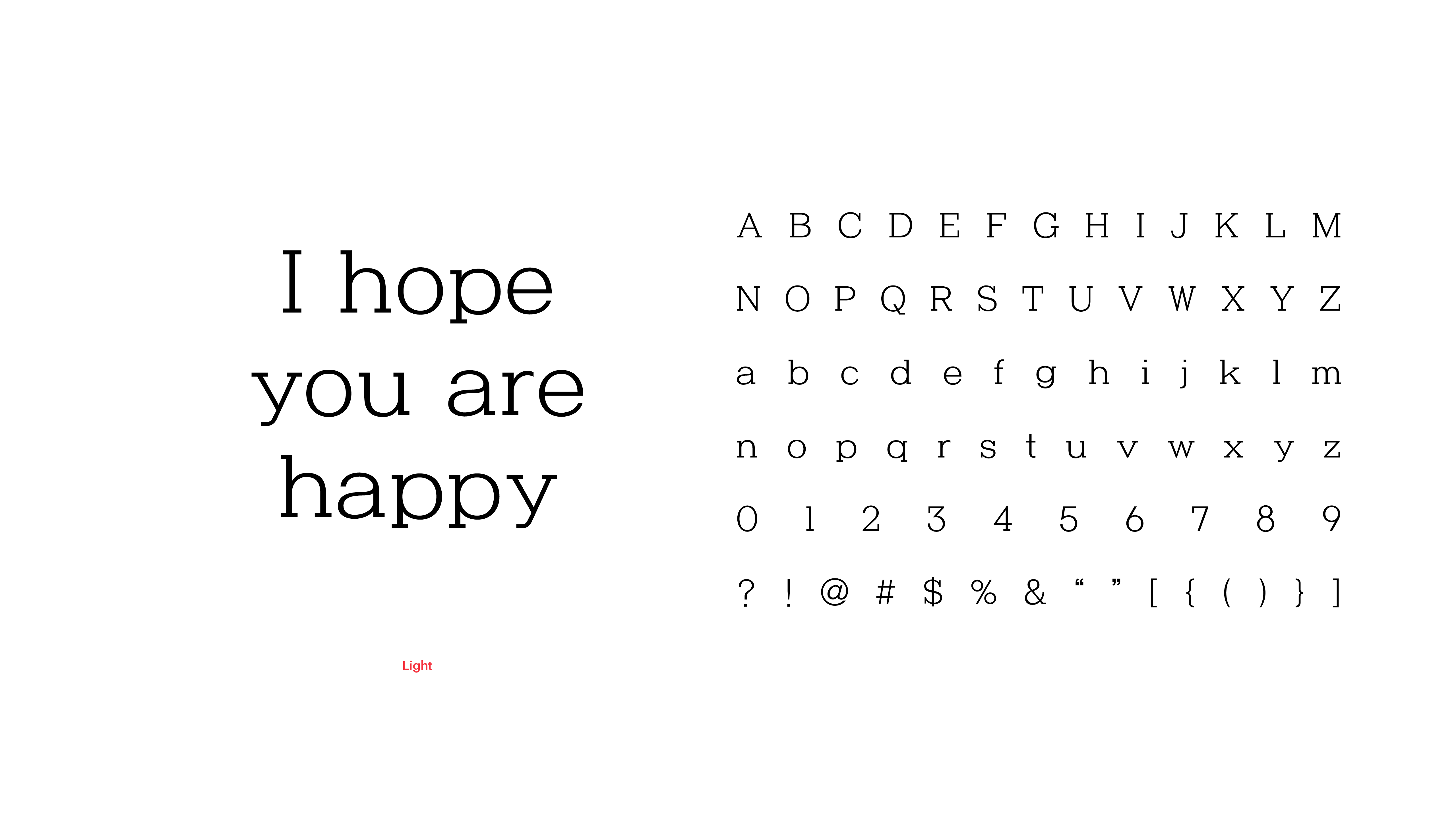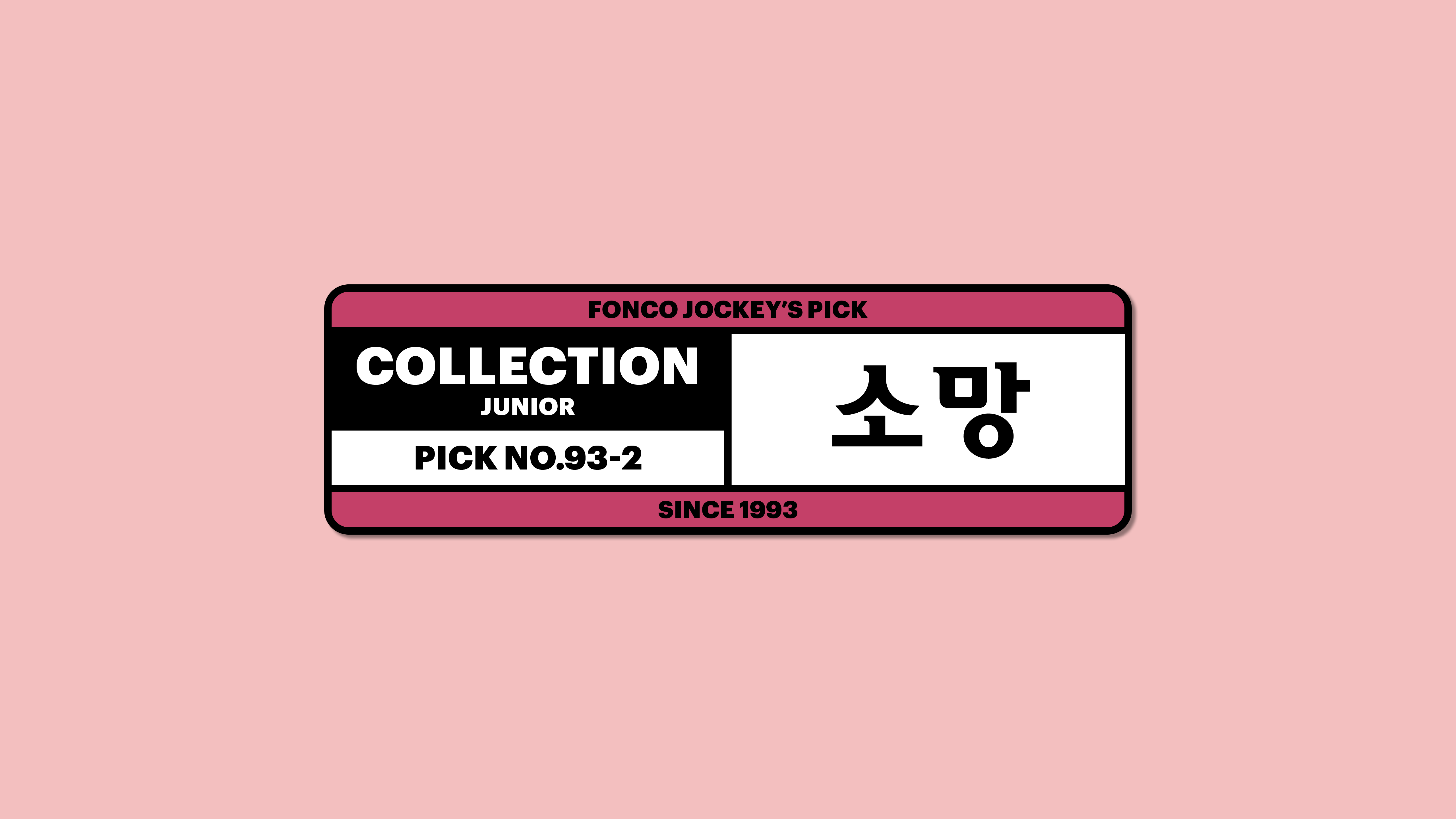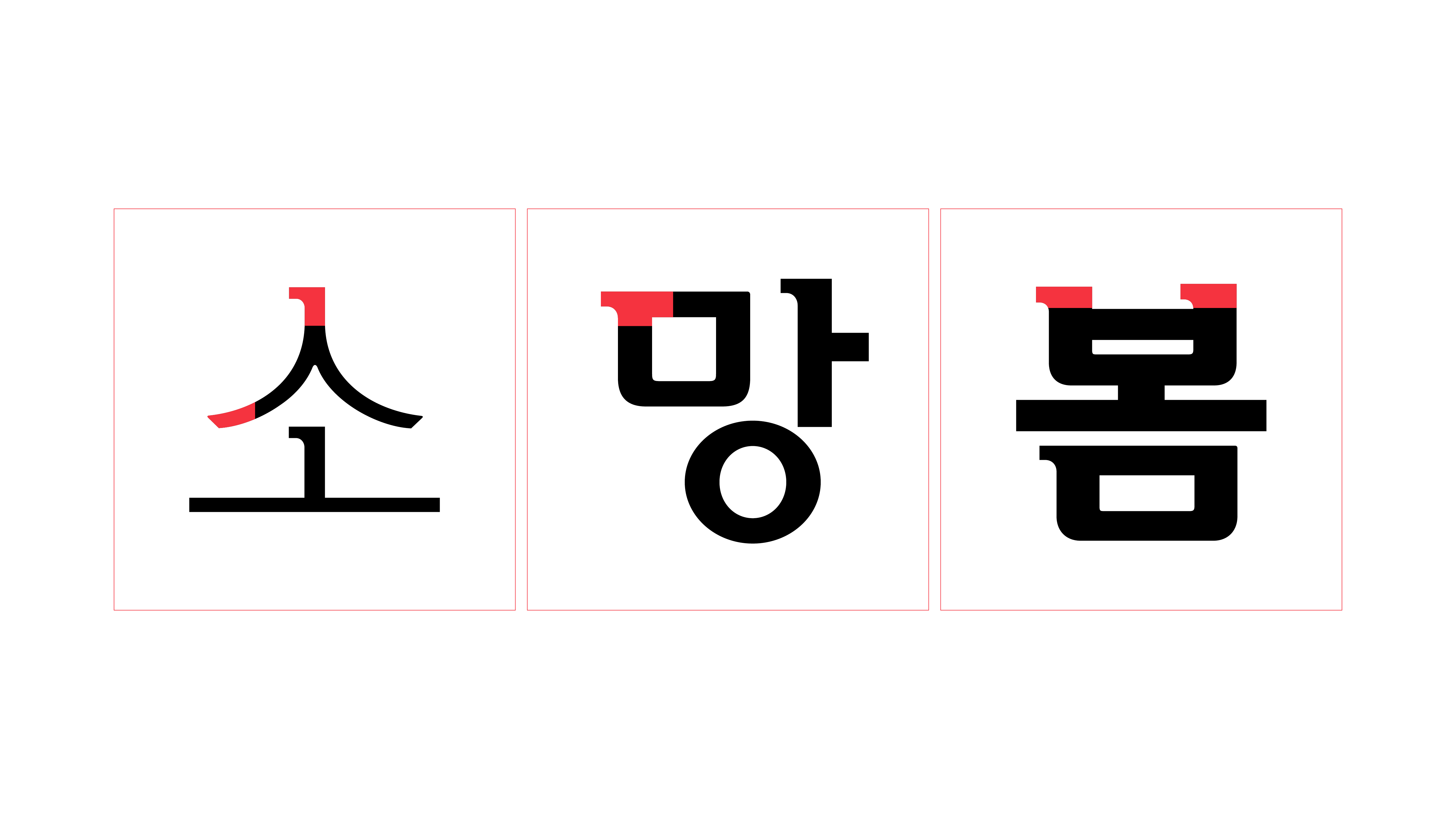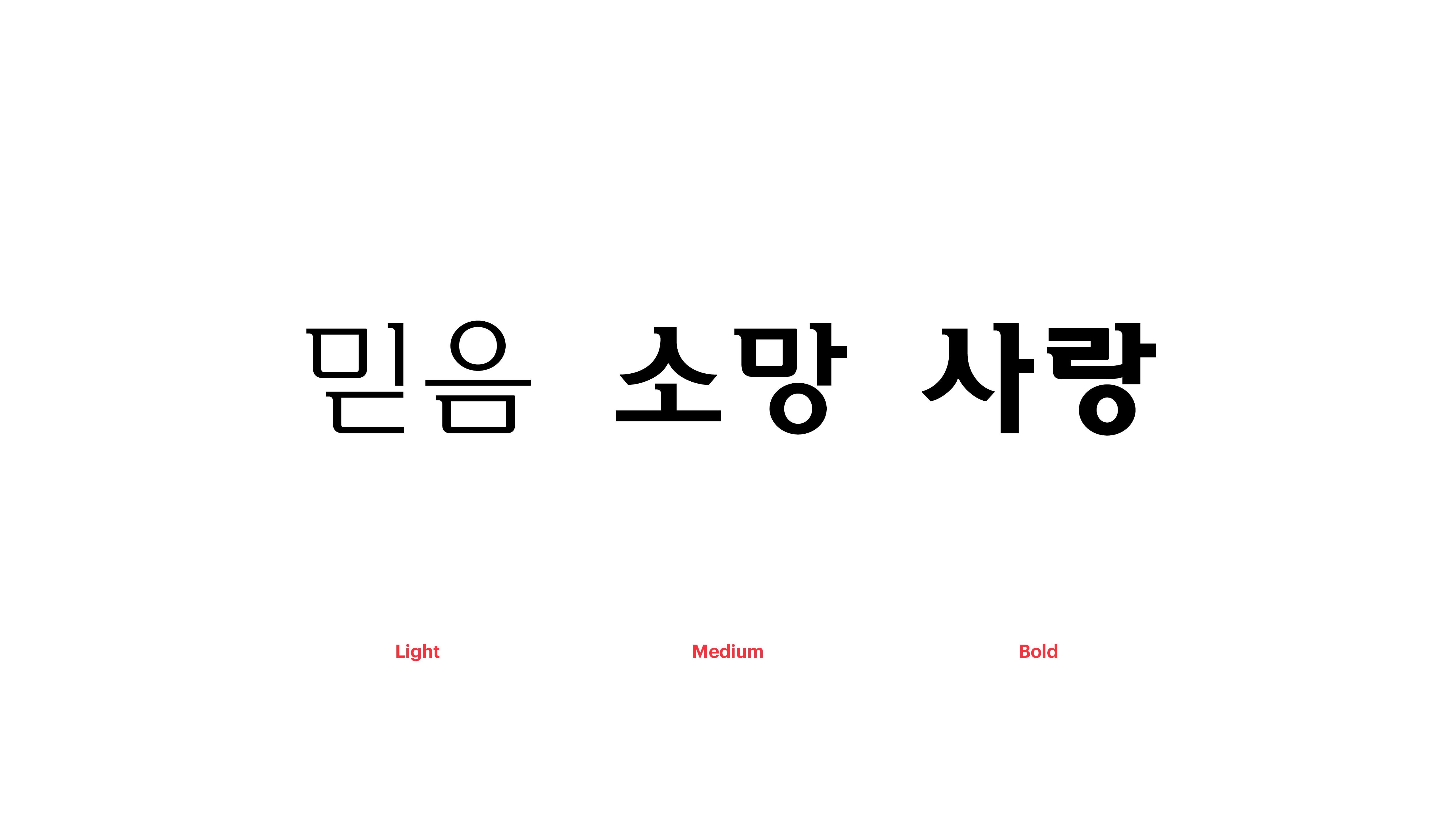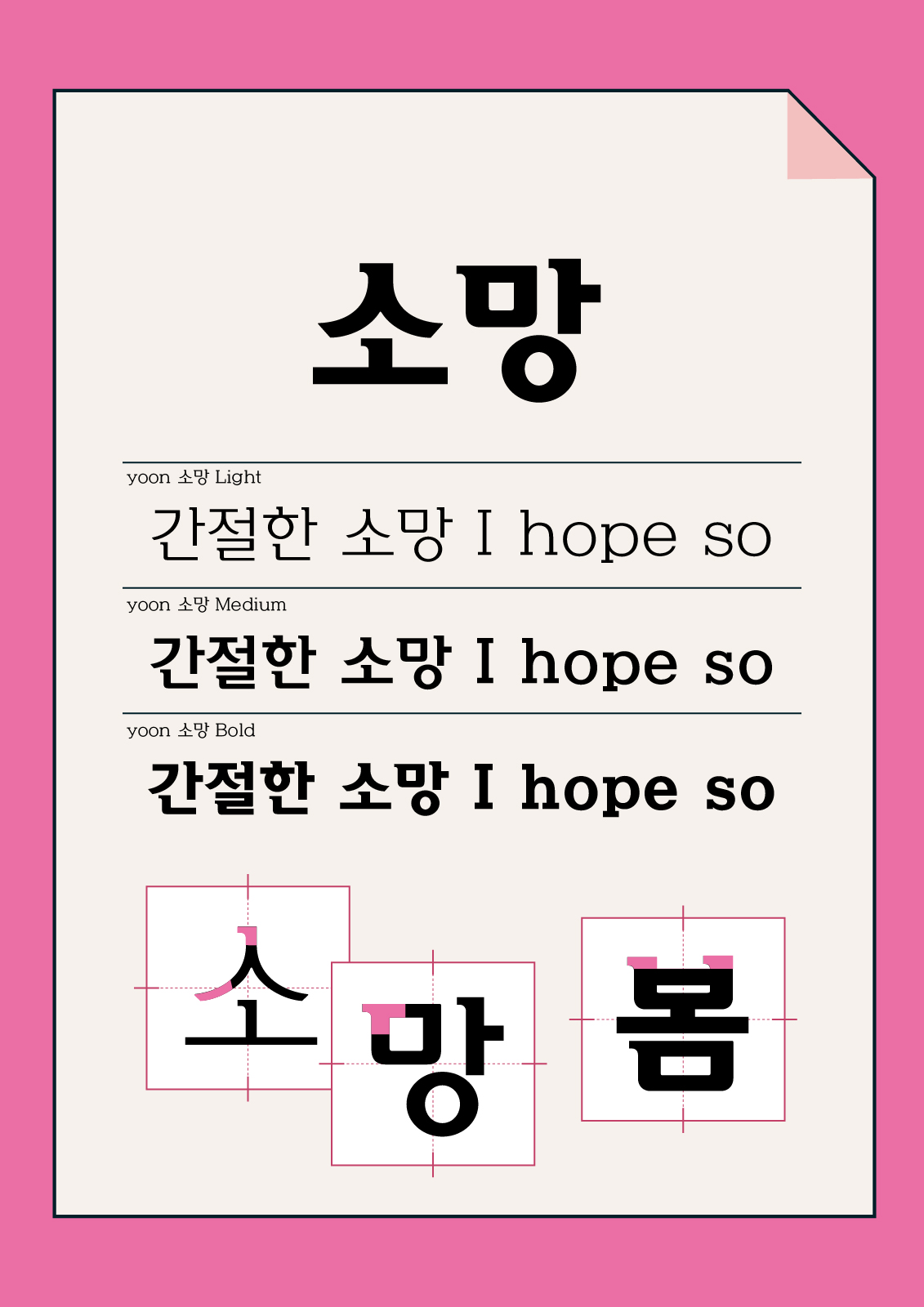
소망
Yoon 소망
소망체에는 마음속에 몽글몽글, 따뜻한 소망이 피어오르는 순간의 부드러움이 그대로 담겨 있습니다. 깔끔한 직선 구조에 부드러운 부리를 더해 금방이라도 솟아오를 것만 같은 이야기들을 적어 내려가기에 안성맞춤이지요. 누군가에게 마음속 간절한 소망을 이야기하고 싶은 날, 소망체와 함께하세요.